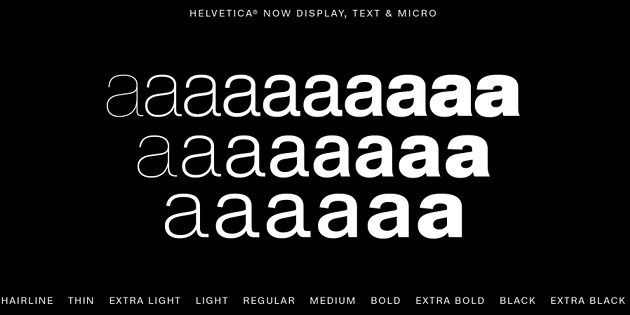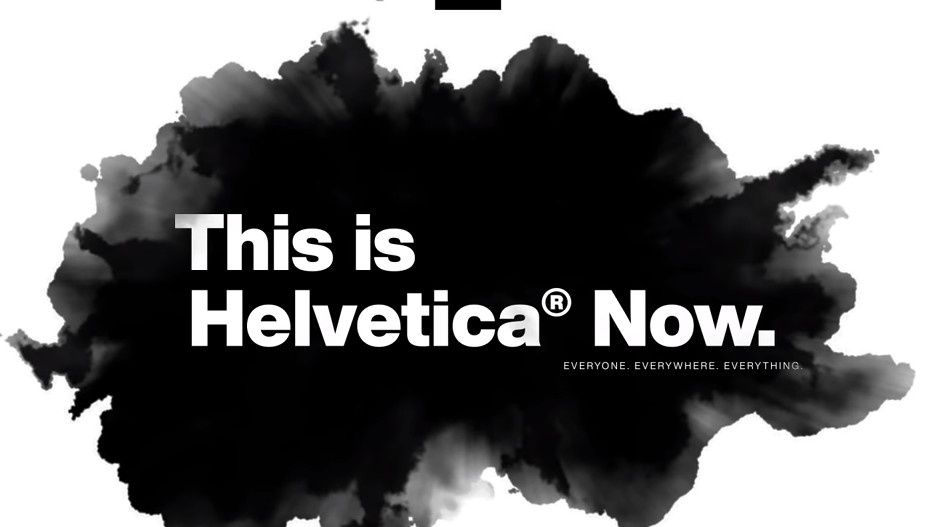
Helvetica Now, czyli wielki (?) powrót legendy
Helvetica Now to nowa wersja fontu, którego nikomu nie trzeba przedstawiać. Jest prosty, czytelny, a przy tym bardzo estetyczny.
Helvetica to font, który widział chyba każdy, choć niekoniecznie musi sobie zdawać z tego sprawę. Fakty są jednak takie, że jest on bardzo często używany, także przez te największe marki. Przez ostatnie trzy dekady zdążył się on nieco zestarzeć i dlatego też studio Monotype stworzyło jego nową wersję, z dopiskiem Now.
Historia Helvetiki, wtedy jeszcze jako czcionki, sięga lat 50. ubiegłego stulecia. Zdigitalizowała ją firma Adobe w 1985 roku i od tego czasu właściwie niewiele się zmieniło. Efekt jest taki, że choć wciąż jest to font, który ładnie wygląda i jest przyjemny w czytaniu, jego skalowanie nie zawsze kończy się sukcesem. Niektóre firmy postanowiły zatem stworzyć własne rozwiązania bazujące na tej klasyce, ale Monotype chce zadbać o to, by marka nie zginęła.
Helvetica Now to rodzina 16 fontów w 3 „rozmiarach” (Micro, Display oraz Text). Za jej zaprojektowanie odpowiada studio Monotype, którego najbardziej znanym dziełem jest Times New Roman. W przeciwieństwie do niego, w tym przypadku mówimy oczywiście o kroju bezszeryfowym.
Helvetica Now Micro ma znaleźć zastosowanie na urządzeniach z małymi ekranami (takich jak smartfony), wariant Display ma być wykorzystywany w reklamach i na banerach, a wersja Text ma być wybierana przede wszystkim wtedy, gdy chodzi o dłuższe materiały tekstowe.
Twórcy przekonują, że dzięki dobrze przemyślanemu projektowi oraz szerokiemu katalogowi opcji, projektanci pokochają ten nowy font i będą chcieli z niego korzystać. Na oficjalnej stronie możecie się nim pobawić, a tymczasem już zostawiamy was z filmem promującym Helveticę Now: